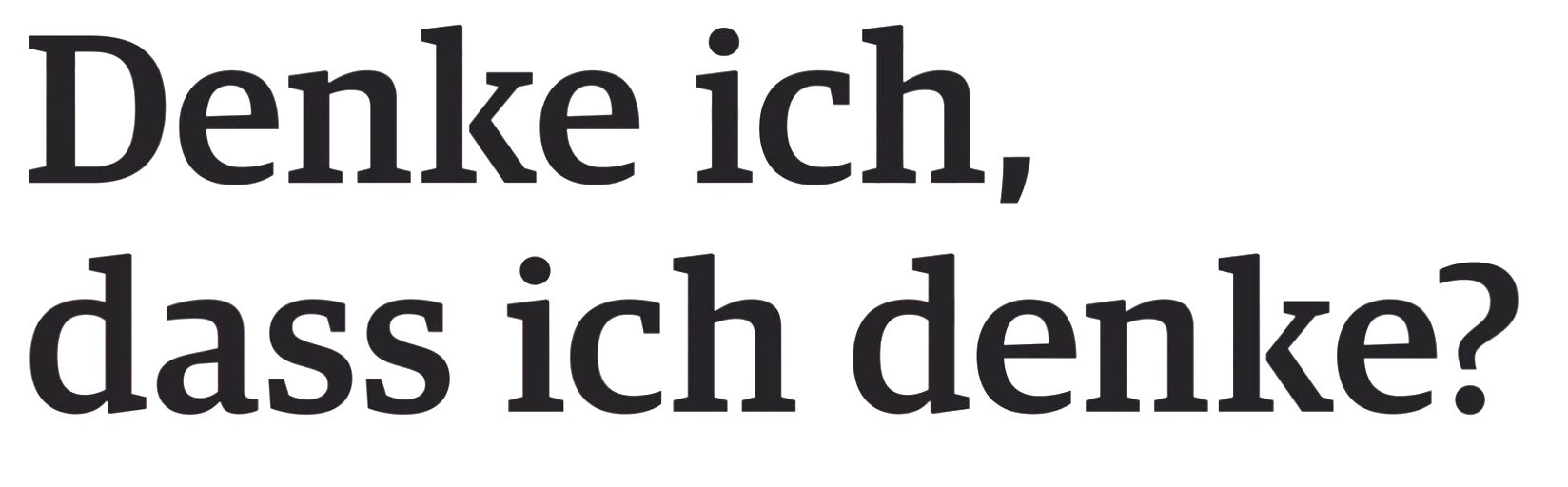
Welche kommt der "Guardian Egyptian" möglichst nahe?
Wahrlich schöne Schrift, die Guardian, besonders die Egyptian. Kennt ihr eine sehr ähnliche?
Kennt ihr eine sehr ähnliche?
Mit welchem Ziel?
Edit: Mir fiel halt spontan die Merriweather ein, falls es eine kostenlose sein soll.
Wir müssen zunächst mal ein paar Dinge ausprobieren, daher wäre eine kostenfreie oder -günstige ideal.
Vielleicht habt ihr ja auch die Meta Serif im Haus, wenn es erstmal nur um einen Test gehen soll. An der hat neben Erik Spiekermann und einigen anderen auch Christian Schwartz (Guardian) mitgewirkt. Ich denke, die passt bzgl. x-Höhe noch etwas besser als die Brando. Nur das g tanzt halt ziemlich aus der Reihe.
Edit: Und die Stag von Christian Schwartz ist auch ziemlich nah an der Guardian Egyptian dran …